چرا تسلط بر فونتهای لایه باز برای هر طراح حیاتی است؟
آیا تابهحال برایتان پیشآمده که طرحی را ببینید و با خود فکر کنید: (چطور این تایپوگرافی یا فونت چنین فرم منعطفی دارد؟) در دنیای گرافیک حرفهای، تفاوت میان یک اثر مبتدی و یک طراحی خیرهکننده، در جزئیات تایپوگرافی نهفته است. آموزش استفاده از فونتهای لایه باز دقیقاً همان حلقه مفقودهای است که به شما اجازه میدهد از محدودیتهای فونتهای معمولی فراتر بروید. اگر گرافیست یا ادیتور هستید، میدانید که استفاده از فونتهای ثابت گاهی دست شما را برای خالقیت میبندد، اما با یادگیری تکنیکهای کار با فونتهای لایه باز، شما صاحب قدرت تغییر در تکتک منحنیها و کشیدگیهای حروف خواهید شد.
فونتهای لایه باز چیست و چرا باید از آنها استفاده کنیم؟
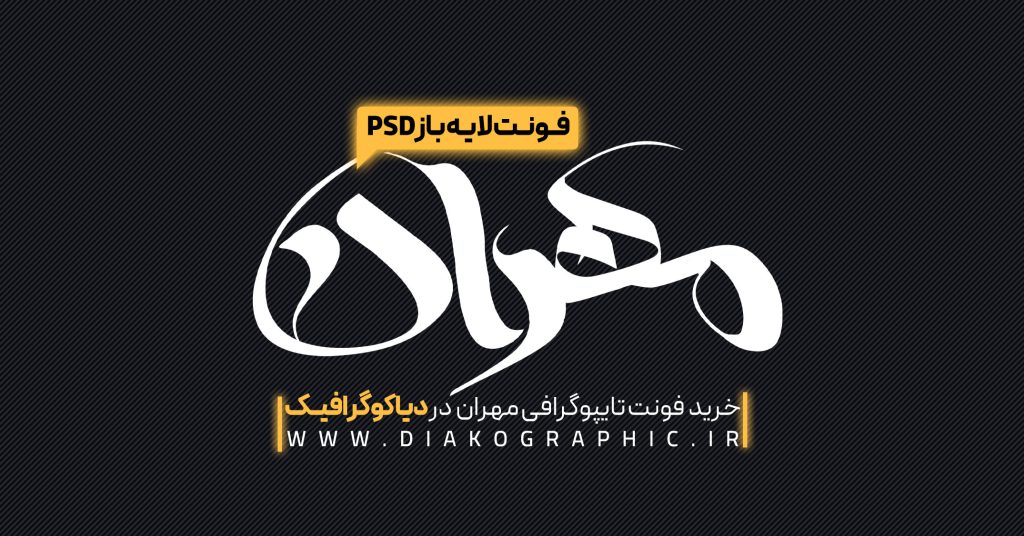
فونتهای لایه باز (Fonts Layer-Open )یا به عبارتی فایلهای وکتوری تایپوگرافی، به شما اجازه میدهند تا بهجای محدودشدن به کاراکترهای آماده، به لایههای تشکیلدهنده حروف دسترسی داشته باشید. این یعنی هر حرف، یک وکتور قابلویرایش در نرمافزارهایی مثل فتوشاپ یا ایلوستریتور است. برخلاف فونتهای معمولی (otf/ttf )که تغییر در آنها دشوار است، فونتهای لایه باز به شما آزادی عمل میدهند تا با تغییرات جزئی، بهترین فونت های فارسی مذهبی یا فانتزی را برای پروژههای خود شخصیسازی کنید. استفاده از این فونتها باعث میشود خروجی نهایی شما منحصربهفرد باشد و هیچ شباهتی به طرحهای آماده و تکراری نداشته باشد.
آموزش گامبهگام کار با فونتهای لایه باز در فتوشاپ و ایلوستریتور
طریقه استفاده از فونتهای لایه باز بسیار ساده و راحت است. این فونتها با فرمت psd عرضه میشود و همین نکته باعث شده تا استفاده از آنها در بستر برنامههایی مانند فتوشاپ و یا ایلوستریتور بسیار راحت باشد. در برنامه فتوشاپ شما میتوانید با کلیککردن بر روی فایل هر فونت، آن را در فتوشاپ بازکرده و باتوجهبه پروژه خود آن را تغییر دهید. در نرمافزار ایلوستریتور، باتوجهبه وجود ابزارهای بیشتر، میتوانید تغییرات دقیقتر و گستردهتری به فونت خود بدهید.
کاربرد فونتهای لایه باز در پروژههای حرفهای
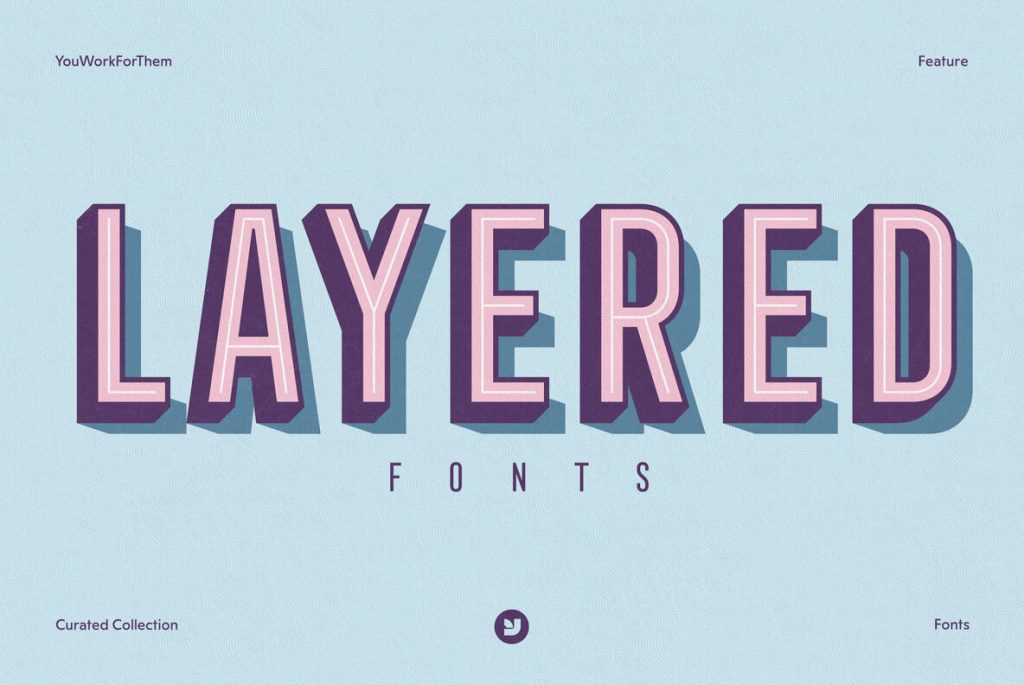
بسیاری از برندهای بزرگ ایرانی و جهانی که امروزه لوگوتایپهای ماندگاری دارند، از همین میکنند. برای مثال، در طراحی بهترین فونتهای فارسی مذهبی که برای بنرهای هیئات یا پوسترها استفاده میشود، طراحان حرفهای ابتدا یک فونت پایه را انتخاب کرده و سپس با استفاده از تکنیکهای لایه باز، کشیدگیها و چرخشهای خاصی به حروف میدهند تا حس معنوی و سنتی بیشتری به طرح بدهند. یا در دنیای فشن و پوشاک، تغییر در پهنای حروف با استفاده از فایلهای لایه باز، باعث میشود لوگوی برند شما به یک اثر هنری مدرن تبدیل شود. آموزش استفاده از فونتهای لایه باز به شما کمک میکند تا این فرایند پیچیده را به یک روتین ساده و سریع تبدیل کنید.
کلام آخر
یادگیری آموزش استفاده از فونتهای الیه باز تنها یک مهارت جانبی نیست، بلکه مسیری برای تبدیل شدن از یک “اپراتور نرمافزار” به یک “طراح هوشمند” است. با تسلط بر این تکنیک، شما دیگر محدود به چیزی که فونت به شما دیکته میکند نیستید؛ بلکه شما هستید که به فونت میگویید چگونه ظاهر شود.فراموش نکنید که: .1 همیشه لایهها را نامگذاری کنید تا در پروژههای بزرگ دچار سردرگمی نشوید. .2 از ترکیب لایهها با استفاده از Modes Blending نترسید؛ خالقیت در لایهها نهفته است. .3 برای پروژههای چاپی، حتماً از حالت Vector در ایالستریتور استفاده کنید تا کیفیت لایهها در ابعاد بزرگ افت نکند.
سؤالات متداول
تفاوت اصلی فونت الیه باز با فونتهای سری Variable چیست؟
فونتهای Variable اجازه تغییر ضخامت و عرض را بهصورت پیوسته میدهند، اما فونتهای الیه باز به شما اجازه میدهند عناصر کاملاً متفاوتی(مثل سایه، خط دور یا تزئینات) را به حرفاضافه کنید.
آیا استفاده از این فونتها در طراحی لوگو باعث سنگینشدن فایل میشود؟
اگر لایهها را بهدرستی مدیریت کنید و خروجی را بهصورت Vector بگیرید، تأثیر ناچیزی بر حجم فایل خواهد داشت.